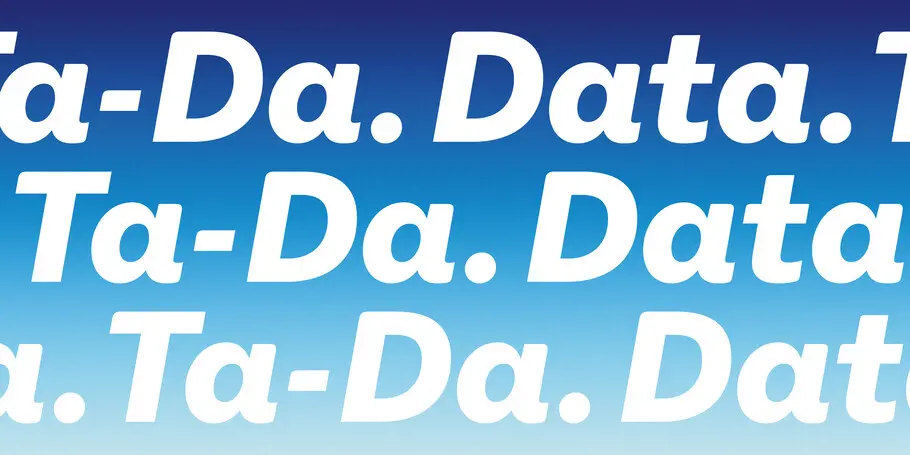
Des polices plus conviviales depuis la pandémie.
Phil Garnham, directeur de la création typographique, s’est entretenu en mai avec The Economist à propos de l’impact de la pandémie sur la typographie. Retraçant cette année sans précédent, The Economist et Phil ont exploré comment cette période a poussé les polices de caractères à devenir plus conviviales pour leur public.
S’il est encore trop tôt pour connaître l’influence de la pandémie sur l’art et le design, il y a un changement que l’on remarque déjà : celui de la typographie. Les événements historiques sismiques peuvent secouer la créativité et l’amener dans d’autres directions. L’éruption d’un volcan indonésien en 1815 avait causé d’étranges phénomènes météorologiques autour du globe, inspirant un nouveau genre de fiction gothique. De la dévastation de la Première Guerre mondiale est né le modernisme, avec des innovations en littérature, en art – et en typographie. Gill Sans, une police fraîche et avant-gardiste créée par Eric Gill en 1926, incarne l’après-guerre et son désir de nouveauté.
Lorsqu’on regarde un panneau ou un logo, on pense tout simplement lire des mots. Mais la manière dont ceux-ci sont écrits vaut tout autant que ce qu’ils disent. La typographie est l’équivalent visuel du ton d’une voix. Vous n’écririez pas une invitation à une fête en Times New Roman ou des excuses sincères en Comic Sans. Dans l’articulation de l’identité d’une entreprise, les polices de caractères jouent un rôle plus grand qu’aucun autre élément de design.
Lorsque le monde change, ce que l’on souhaite dire change aussi. C’est pourquoi la pandémie a déjà influencé la typographie de marque. Les polices unies, ordonnées et fonctionnelles cèdent la place à davantage de rondeur, de douceur, d’expression. La tendance a émergé quelques années plus tôt, sous l’impulsion d’entreprises ayant des identités sciemment ludiques comme Duolingo ou Mailchimp. Et elle s’est accélérée au cours de l’année dernière. En Grande-Bretagne, Currys PC World, un magasin d’électroménager, et Zoopla, un site Web immobilier, ont abandonné leurs styles impassibles pour des caractères plus originaux. Pour vendre une machine à laver de nos jours, il faut des descendants hauts en couleur sur les «g».
Le dernier grand nom à suivre le mouvement est O2, une compagnie de télécommunications. La marque abandonne Frutiger, l’humaniste sans serif ordinaire utilisée depuis 2002, et se tourne vers On Air, une nouvelle police créée sur mesure par Monotype (qui a aussi créé le design de la police Milo pour The Economist). Les angles ronds et les éléments calligraphiques de On Air suggèrent une note humaine, explique Phil Garnham. L’objectif est d’apporter de la chaleur et de la personnalité aux écrits marketing d’O2. L’effet des polices comme On Air est «subliminal», selon Phil Garnham, ce qui nous rappelle à la puissance avec laquelle une typographie peut influencer notre compréhension des mots. Pourtant, depuis le début du siècle, les marques ont été coincées dans une routine typographique. Sans surprise, internet en est la cause.
Depuis deux décennies, les marques choisissent des polices sans serif génériques pour leur lisibilité sur les écrans, quelles que soient leurs tailles et résolutions. La police sortante d’O2, Frutiger, est souvent considérée comme la police la plus lisible jamais inventée, ce pourquoi on la voit apparaître sur les panneaux d’aéroports partout dans le monde. Bien que la technologie permette aujourd’hui aux designers d’utiliser n’importe quelle police sur un site Web, les marques ont continué à graviter autour de bases froides et géométriques comme Avenir, Gotham et Proxima Nova.
On Air
Les typographies sont l’équivalent visuel du ton d’une voix.
Pourtant, lisible ne veut pas nécessairement dire mémorable – en fait, c’est parfois le contraire. En 2018, les chercheurs du Royal Melbourne Institute of Technology ont constaté qu’avec des polices trop familières, les lecteurs avaient tendance à faire abstraction des mots, tandis qu’ils en gardaient une meilleure mémoire lorsque la lecture impliquait une sorte de «difficulté désirable».
Ils ont créé Sans Forgetica, une police qui omettait certaines parties des traits des lettres et demandait au cerveau un effort pour combler les trous. En la testant sur des étudiants, ils ont découvert que les faits écrits avec cette police étaient plus faciles à retenir que ceux écrits en Arial (bien que d’autres recherches n’aient ensuite trouvé aucune preuve que la Sans Forgetica favoriserait la mémorisation).
Quel que soit leur effet sur la mémoire, les polices fonctionnelles sont en voie de disparition. Cela est en partie dû au fait que les résolutions d’écran se sont améliorées, et les systèmes de design typographiques sont plus perfectionnés. La pandémie est une autre raison, parce qu’elle a changé la manière dont les marques interagissent avec nous. Quand les magasins sont fermés, le matériel marketing écrit – en ligne ou glissé dans une boîte aux lettres – devient plus important. Les polices de caractères ont plus de travail que jamais.
Lisible ne veut pas nécessairement dire mémorable – en fait, c’est parfois le contraire.
Les polices de l’ère pandémique partagent un thème commun : des lignes courbes et des formes rondes. Aoife McGuinness, un consultant en neuroscience pour l’agence marketing HeyHuman, explique que le cerveau pourrait être programmé pour associer certaines formes à certains concepts ou sentiments.
Une étude sur les emballages alimentaires datant de 2017 démontre que les personnes associent les polices arrondies aux goûts sucrés et les lettres anguleuses à l’acidité. Les lignes droites et les angles pointus dégagent solidité et autorité, tandis que les courbes et les cercles apportent douceur, bienveillance et même, convivialité. Les typographies chaleureuses pourraient être un moyen de se rapprocher des consommateurs, en particulier de ceux éprouvant de la solitude en période de confinement. Si vous ne pouvez pas sortir avec vos amis de la vie réelle, pourquoi ne pas devenir ami avec votre fournisseur de haut débit ?
Les polices de l’ère pandémique partagent un thème commun : des lignes courbes et des formes rondes.
Nous avons également eu tout notre temps pour réfléchir. Les consommateurs sont plus soucieux de la durabilité et de la diversité qu’en 2019, et les entreprises doivent y prêter attention. Si les caractères géométriques froids évoquent une certaine autorité, voire de l’arrogance, la transition vers des formes de lettres plus rondes et chaleureuses reflète une approche plus humble et respectueuse. Pour les marques, ajuster leur police est un moyen de garder une longueur d’avance.